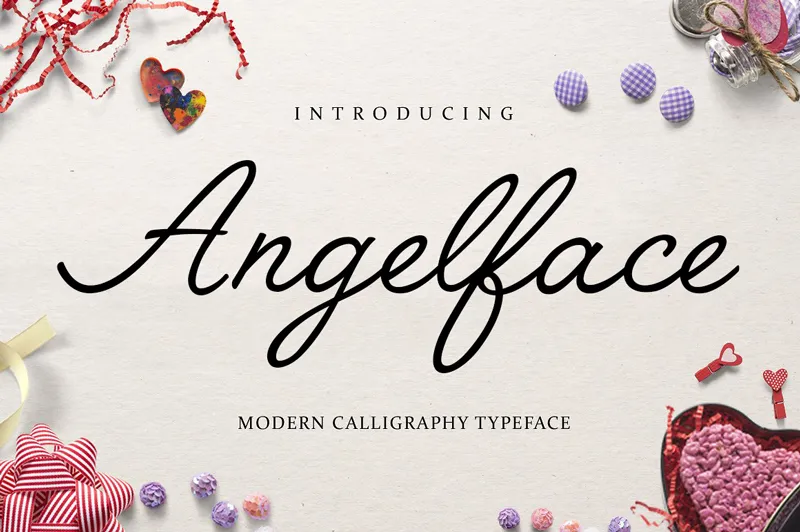
Angelface Script Font – Download Grátis
Através do trabalho meticuloso de Mario Arturo, a Fonte Angelface Script oferece uma experiência única para os designers e criadores de conteúdo. Inspirada no estilo suave e moderno das escritas chamadas, essa nova fonte traz um ar descontraído que se destaca entre as demais. Desenvolvida baseada em Lariata Typecafe e inspirada nos estilos de escrita do livro Schreibschriften/Script Types da Novum Press de 1993, a Fonte Angelface incorporou pontuação para um documento que originalmente se concentrava apenas nas letras e números. Ao longo deste processo meticuloso, Arturo adicionou os elementos necessários para tornar essa fonte uma opção indispensável para designers e criadores de conteúdo em busca de uma escrita chamada suave e contemporânea. Composta por Mario Arturo, a Angelface Script se destaca como uma versão refinada do estilo chamado, oferecendo aos usuários um recurso visual inigualável para seus projetos.